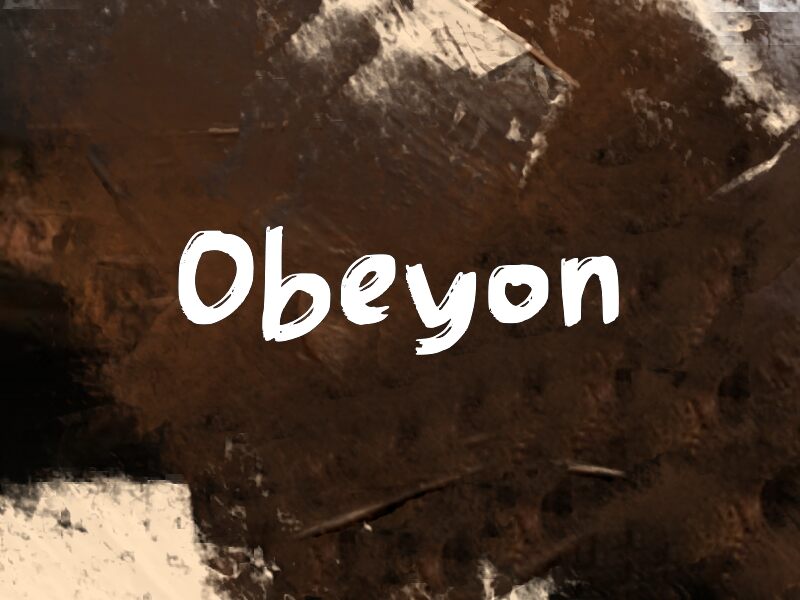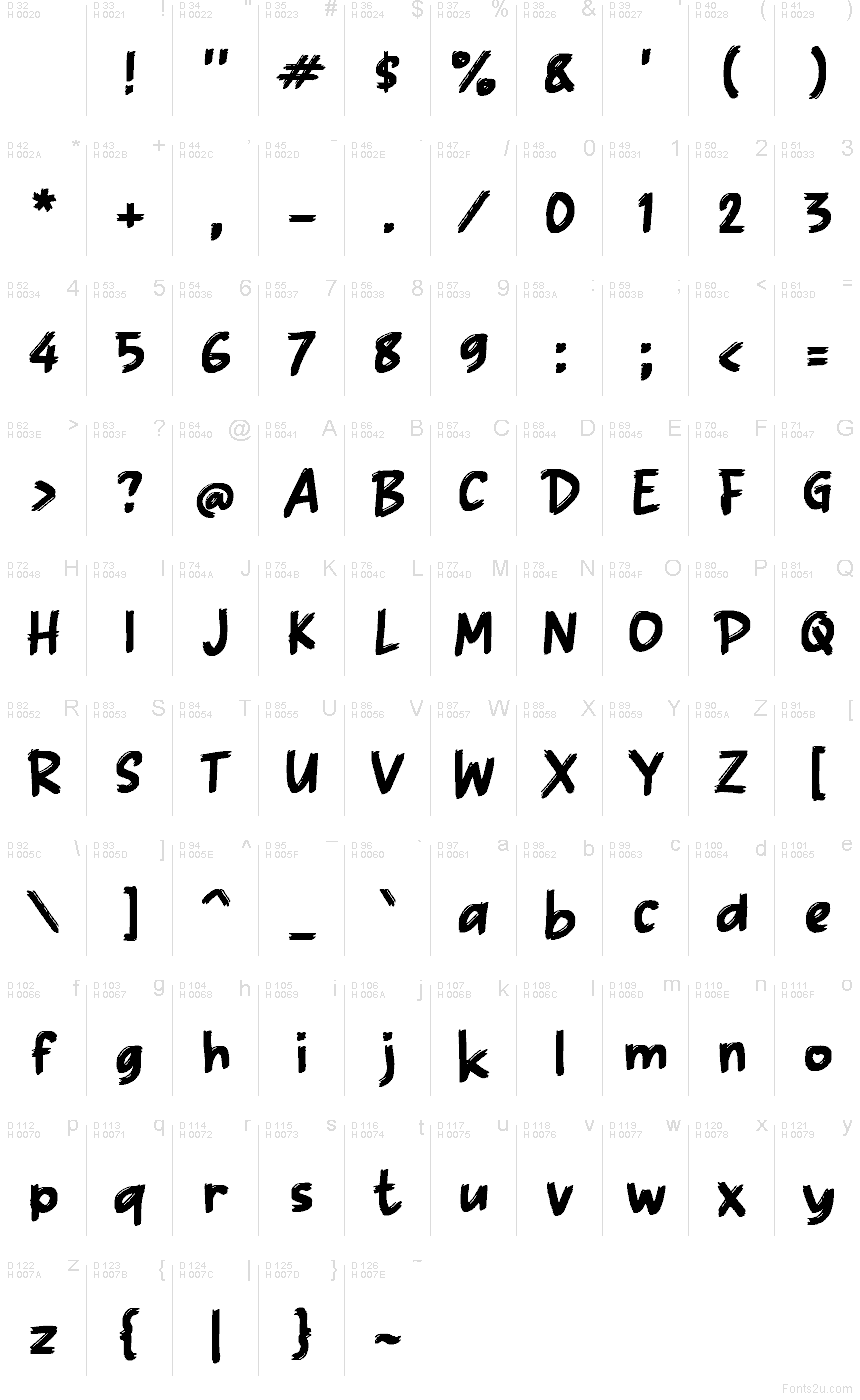
Obeyon od Wep to darmowy krój pisma typu dry-brush o luźnym, ręcznie malowanym charakterze. Litery są szerokie i lekko nierówne, z postrzępionymi krawędziami, grubymi pociągnięciami i szybkim rytmem pędzla, co nadaje napisom surowej energii, dalekiej od wygładzenia.
Dzięki temu ten darmowy font jest naturalnym wyborem do nagłówków na plakatach, opraw graficznych muzyki, wzorów streetwearowych, okładek zinów, brandingu kawiarni czy krótkich tytułów w mediach społecznościowych. Świetnie sprawdza się również w nazwach na opakowaniach czy monogramach, ponieważ tekstura pędzla i zaokrąglone kształty nadają nawet kilku literom żywy, ręcznie wykonany wygląd.